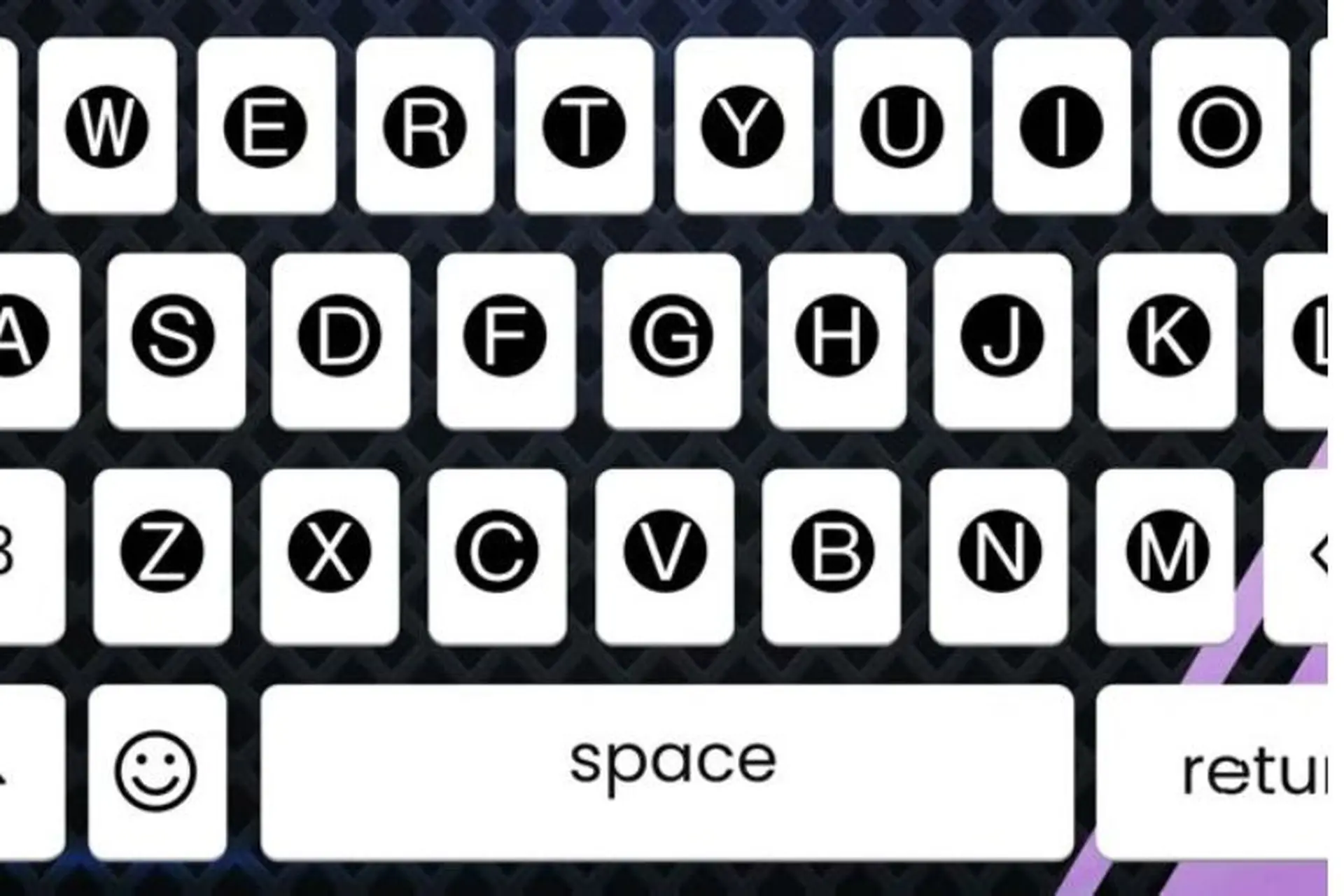
Fonts Keyboard: Khám phá những tính năng thú vị giúp bạn biến hóa phong cách giao tiếp hiệu quả
Fonts Keyboard là ứng dụng gì?
Fonts Keyboard là một loại ứng dụng bàn phím ảo dành cho các thiết bị di động như điện thoại thông minh và máy tính bảng. Điểm đặc biệt và cốt lõi của ứng dụng này là nó không thực sự thay đổi "phông chữ" (font) theo cách truyền thống (như trong Microsoft Word) mà nó sử dụng các ký tự Unicode đặc biệt để tạo ra các kiểu chữ độc đáo.
Cụ thể hơn, khi bạn gõ chữ "Hello", ứng dụng sẽ chuyển đổi nó thành các chuỗi ký tự Unicode trông giống như chữ được cách điệu, chẳng hạn như "𝐇𝐞𝐥𝐥𝐨" (in đậm), "𝓱𝓮𝓵𝓵𝓸" (viết tay) hoặc "🄷🄴🄻🄻🄾" (khoanh tròn). Vì các ký tự này là một phần của bộ mã Unicode tiêu chuẩn, chúng có thể hiển thị chính xác trên hầu hết các nền tảng và ứng dụng (như Facebook, Instagram, TikTok, Zalo) mà không yêu cầu người xem phải cài đặt cùng một ứng dụng bàn phím.
Mục đích chính của Fonts Keyboard là giúp người dùng cá nhân hóa và làm nổi bật các đoạn văn bản của mình, từ dòng trạng thái, tiểu sử (bio) trên mạng xã hội, tin nhắn cho đến tên trong game. Ngoài các kiểu chữ, nhiều ứng dụng còn tích hợp thêm kho biểu tượng, Kaomoji (biểu cảm ký tự Nhật) và các ký tự nghệ thuật khác để làm phong phú thêm nội dung.
Những tính năng chính của Fonts Keyboard
Kho phông chữ đa dạng
Đây là tính năng cốt lõi và hấp dẫn nhất của Fonts Keyboard. Ứng dụng cung cấp quyền truy cập vào một bộ sưu tập khổng lồ các kiểu phông chữ (font) độc đáo và sáng tạo mà không có sẵn trên bàn phím hệ thống tiêu chuẩn. Các phông chữ này rất đa dạng về phong cách, bao gồm chữ viết tay mềm mại, chữ đậm, chữ nghiêng, chữ cổ điển (gothic), chữ trang trí, chữ vui nhộn và nhiều kiểu cách khác.
Người dùng có thể dễ dàng duyệt qua hàng trăm, thậm chí hàng nghìn tùy chọn để tìm ra phông chữ phù hợp với tâm trạng, nội dung tin nhắn hay phong cách cá nhân của mình, giúp văn bản trở nên mới lạ và bắt mắt hơn.
Dễ dàng chuyển đổi phông chữ
Một trong những yếu tố quan trọng làm nên sự tiện lợi của Fonts Keyboard là khả năng chuyển đổi giữa các phông chữ một cách nhanh chóng và mượt mà ngay trong lúc gõ. Thay vì phải vào cài đặt hay copy-paste từ nơi khác, người dùng thường chỉ cần cuộn hoặc chạm vào danh sách các phông chữ được hiển thị trực tiếp trên hoặc gần bàn phím.
Điều này cho phép bạn thay đổi kiểu chữ ngay lập tức cho từng từ, câu hoặc đoạn văn mà không làm gián đoạn quá trình nhập liệu. Từ đó giúp việc thử nghiệm các phong cách khác nhau trở nên đơn giản và hiệu quả.
Tích hợp rộng rãi với các ứng dụng
Fonts Keyboard được thiết kế để hoạt động liền mạch với hầu hết các ứng dụng trên thiết bị di động có hỗ trợ nhập liệu văn bản thông qua bàn phím hệ thống. Điều này có nghĩa là bạn có thể sử dụng các phông chữ độc đáo này ở rất nhiều nơi, từ các nền tảng mạng xã hội phổ biến.
Ví dụ như Instagram (trong bio, caption, story), TikTok, Facebook, Twitter, Snapchat cho đến các ứng dụng nhắn tin như WhatsApp, Viber, Telegram, ứng dụng ghi chú, email và trình duyệt web. Tính năng này đảm bảo rằng bạn có thể thể hiện cá tính bằng phông chữ độc đáo ở hầu hết mọi nơi bạn giao tiếp bằng văn bản.
Hỗ trợ ký hiệu, biểu tượng đặc biệt
Ngoài phông chữ, Fonts Keyboard còn tích hợp thêm kho tàng các ký hiệu, biểu tượng và hình vẽ đặc biệt. Các yếu tố này có thể bao gồm các đường kẻ trang trí, hình ngôi sao, trái tim, mũi tên cách điệu cũng như các Kaomoji (biểu tượng cảm xúc kiểu Nhật Bản được tạo từ ký tự).
Việc bổ sung các ký hiệu và biểu tượng này giúp người dùng có thêm công cụ để làm sinh động và trang trí cho văn bản của mình, tạo điểm nhấn hoặc truyền tải cảm xúc một cách sáng tạo hơn ngoài chỉ dùng chữ cái thông thường.
Bàn phím emoji cải tiến
Fonts Keyboard tích hợp với bàn phím emoji tiêu chuẩn của hệ thống, đảm bảo người dùng vẫn có thể sử dụng đầy đủ các biểu tượng cảm xúc phổ biến. Một số phiên bản nâng cao còn có thể cải thiện trải nghiệm sử dụng emoji bằng cách sắp xếp khoa học hơn, cung cấp chức năng tìm kiếm nhanh hoặc thậm chí đề xuất các tổ hợp emoji độc đáo hay các hình ảnh nghệ thuật được tạo từ emoji và ký tự.
Tùy chỉnh giao diện bàn phím
Không chỉ thay đổi phông chữ của văn bản, Fonts Keyboard cho phép người dùng tùy chỉnh giao diện của chính bàn phím ảo trên màn hình. Các tùy chọn tùy chỉnh này thường bao gồm thay đổi màu sắc nền, thêm hình ảnh hoặc hình nền cá nhân, điều chỉnh kiểu dáng nút bấm và thậm chí là âm thanh khi gõ phím. Tính năng này giúp người dùng cá nhân hóa công cụ nhập liệu, làm cho trải nghiệm gõ phím trở nên thú vị và phù hợp với sở thích thẩm mỹ của mỗi người.